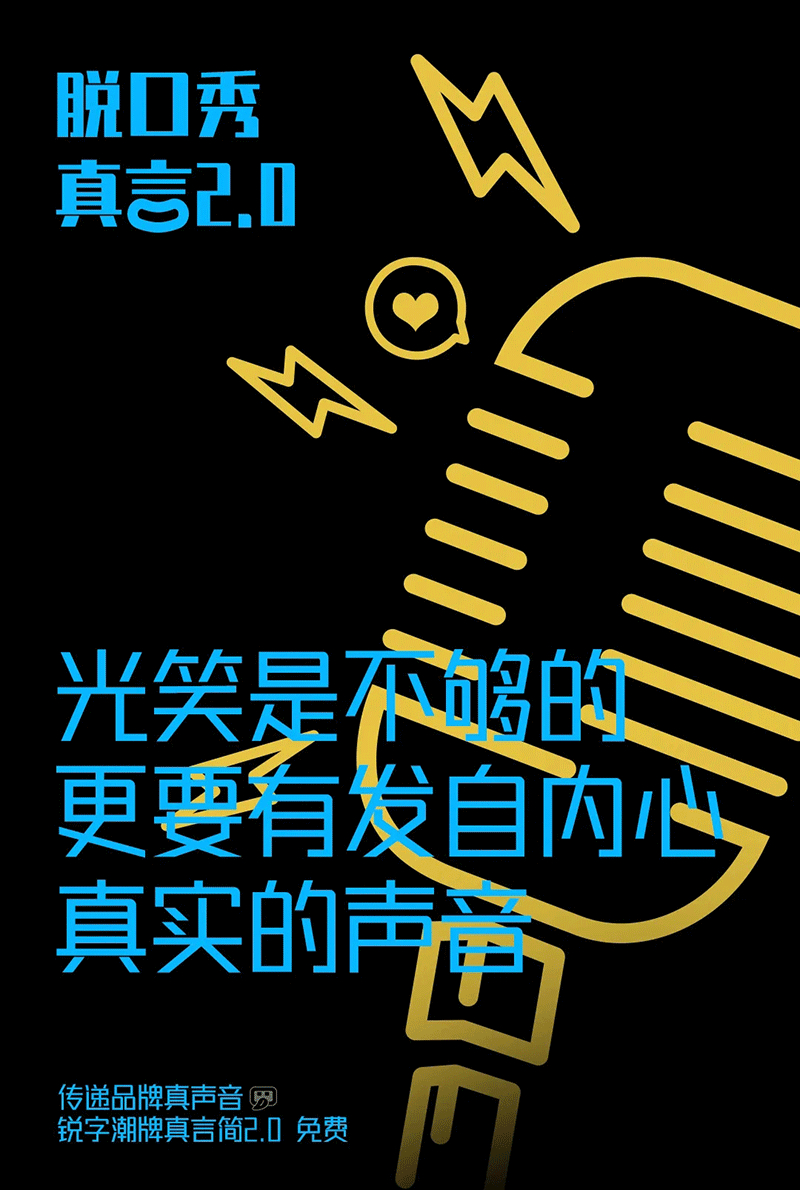
銳字潮牌字庫成立7週年重磅官宣:銳字潮牌真言簡2.0全新升級發佈!免費商用!
本次升級調整字體結構;新增6個字重;增加17個繁體與生僻的常用字,共7672個字符。並支持可變字體!可隨心所欲自由變換,把字體玩出花!現面向社會開放下載,
品牌真言,即品牌靈魂。銳字潮牌真言簡2.0免費,在1.0版本基礎上進行視覺升級,全方位展現品牌信息,更好地傳遞品牌真聲音。
更具呼吸感、通用性更強:銳字潮牌真言簡2.0細體文字,結構乾淨,筆畫移除了粗細對比,因此辨識度更高,字形看起來更加清晰、乾淨。中性的筆畫設計與分隔使得細體文字通用性更強,排版也更有質感,畫面看上去更加輕盈,具有呼吸感,更容易閱讀。
系列化字體、更加潮流、高級:升級後的系列化字體,在保持橫畫不變的基礎上,將豎畫粗細進行變化,隨著字重的減小,橫畫與豎畫粗細對比減弱,增添了字的留白與內部空間感,給人潮流、高級之感。
6字重全方位免費、傳播品牌真聲音:品牌聲音也有跨度,從低聲吟唱到放聲高歌,你的品牌要跨越幾個度?
銳字潮牌真言簡2.0在1.0版本基礎上,衍生出5款系列化字體,共細體、常規、準粗、大粗、特粗、超粗6款字重,全面傳播品牌真聲音。
潮牌可變字體、擁抱變化新世界:本次字體升級的另一個驚喜:新增可變字體技術!將含有字體粗細變化的字體文件,包含在單個字體文件中,從而實現隨意切換,讓字體呈現出不同的形態。
字體自由變換,具有無限延伸的可能性,安裝可變字體文件後,可以通過滑動調節字體的粗細,在這種自由的形態下,設計師可以按照設計需求、喜好來控制字體的使用範圍,讓字體具有無限延伸的可能性。
更靈活的使用場景,全新的視覺體驗,可變字體的應用,突破了傳統字體的限制,比如網頁適配,不同的顯示器設備屏幕比例適配等,讓字體在不同的傳播媒介中可以更靈活地運用。
除此之外,可變字體還擁有更多的創意空間與可能性,為品牌帶來全新的視覺體驗。
潮牌可變字體新紀元,擁抱場景變化新世界:當前,可變字體已成為設計領域的一個熱點,將可變字體運用到多維虛擬世界中,會發生甚麼?
字體應用範圍更加廣泛,適用於文字標題、廣告設計、個性品牌設計推廣、企業宣傳及時尚品牌的設計應用,從電商、產品到視頻、直播等領域,帶給用戶新的體驗和感受。